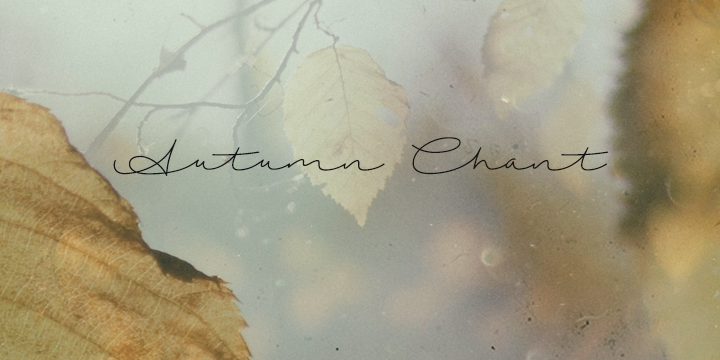
Aqui está uma descrição curta e envolvente para a página de download da fonte ‘Autumn Chant Font’, adaptada ao formato solicitado: A fonte Autumn Chant é um convite para escrever que se assemelha à voz suave das folhas douradas em outono. Criada pelo talentoso designer Hamilton, esta fonte é perfeita para quem busca uma sensação natural e vivaz em projetos de design sem comprometer a legibilidade. Com traços delicados e um tom versátil, Autumn Chant oferece o que há de melhor nas escritas manuscritas. Suave e elegante, ela é ideal para gráficos de marca, editoriais de textos e design gráfico em geral. A autora Hamilton criou uma fonte única, cheia de sutileza e vida. Para usar esta fonte nos seus projetos comerciais ou desfrutar da versão completa, lembre-se: Hamilton oferece opções para doar e entrar em contato através do seu email . Não hesite em explorar este recurso gráfico incrível.